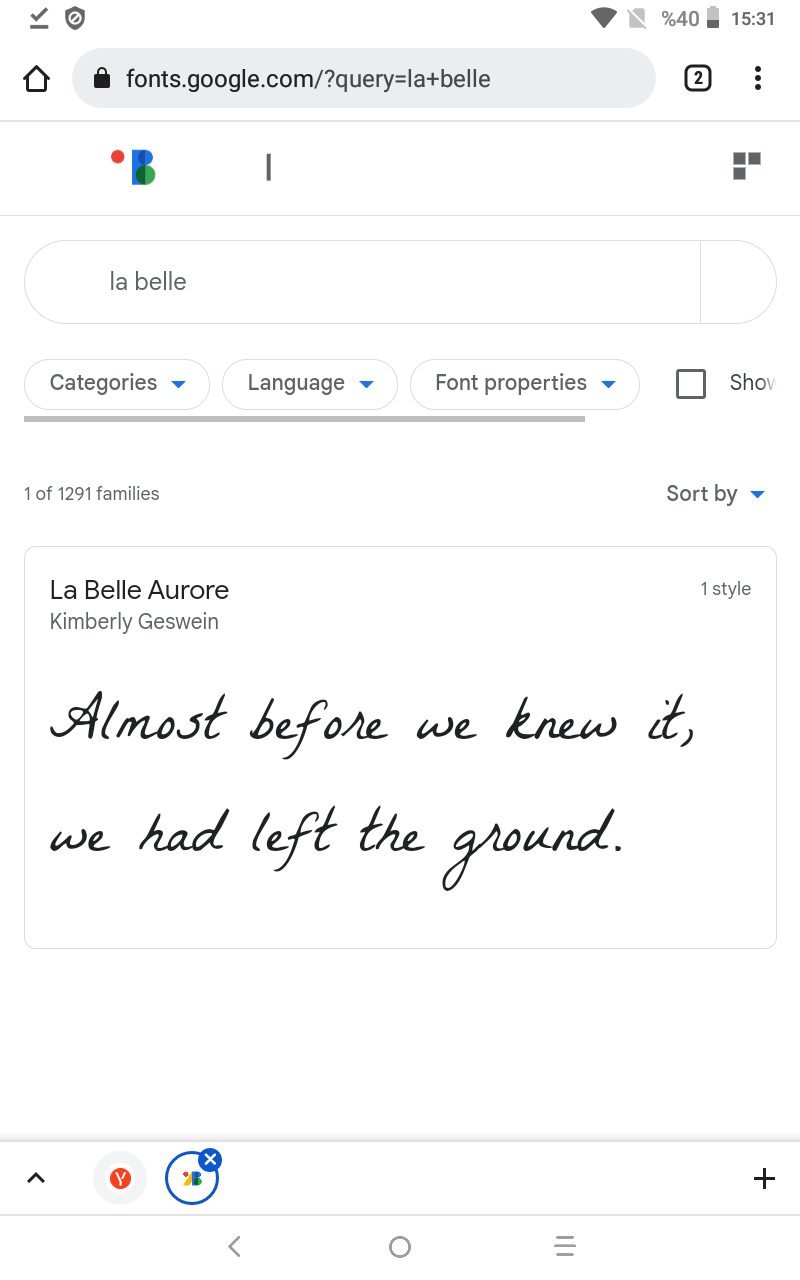
font arıyorum r10+
fontun adı nedir internette aradım ama bulamadım yardımcı olabilecek var mı
yüzde doksan özel tasarım g ve a harfleri hatta a harfini n harfinden yapmış lakin önerim benzer bi kaç font var
Vrubel
Polar Press
Ares
@Eyup; merhaba. Hocam onu bilmiyorum ama ben google fonts içerisinden La Belle Aure önerebilirim: